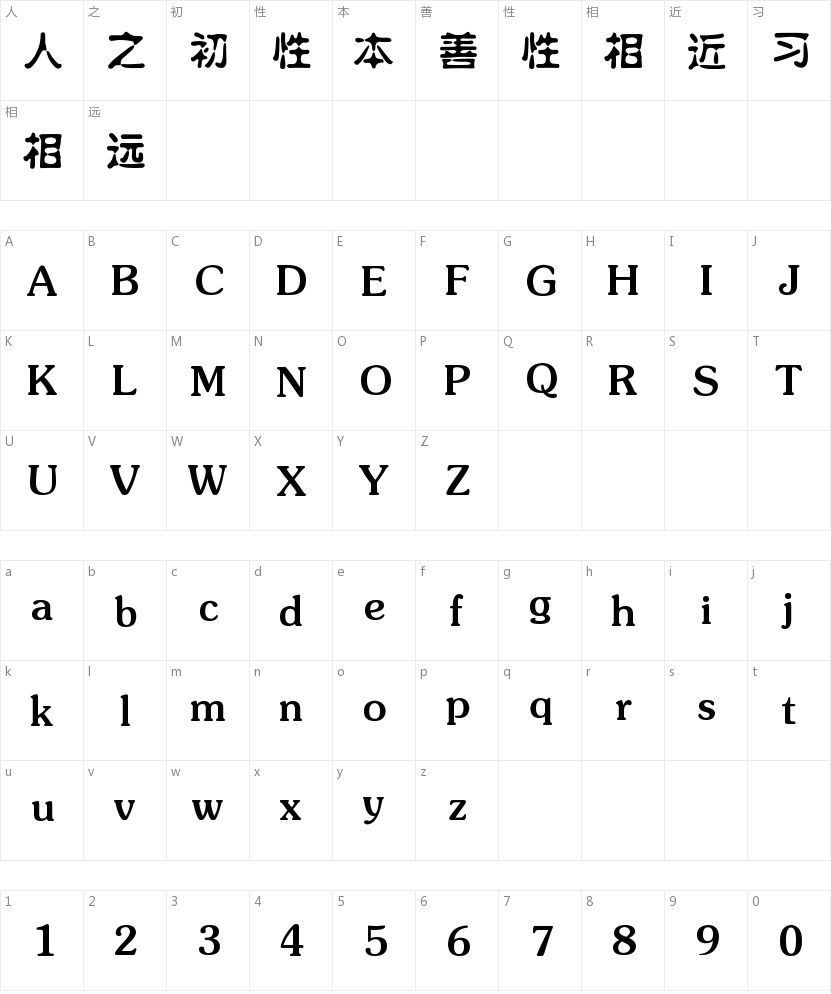
迷你简水柱
迷你简水柱是一种简洁的汉字字体,由中国字体设计师潘玉英创作,于2017年发布。它是一种极简风格的字体,字体的笔画简洁而精致,字体的结构紧凑而清晰,具有极佳的可读性。迷你简水柱字体可以用于多种印刷和网络应用,如报纸、杂志、广告、海报、标志、网站等。
迷你简水柱是一款非常不错的手写艺术字体,具有很好的视觉感,适合于文化类的宣传设计、商业类品牌的广告和产品包装设计以及个性化文字排版等较多场景。